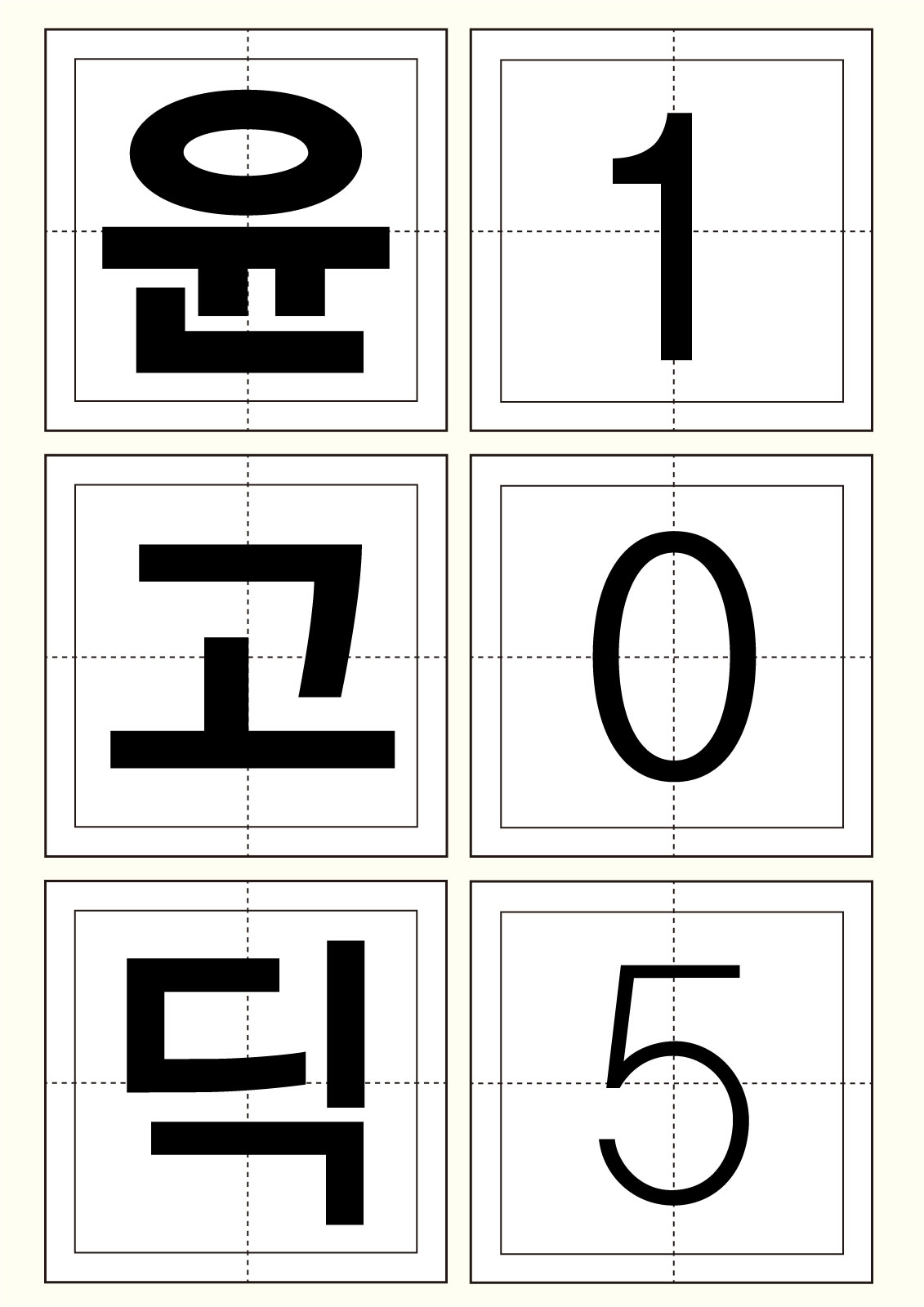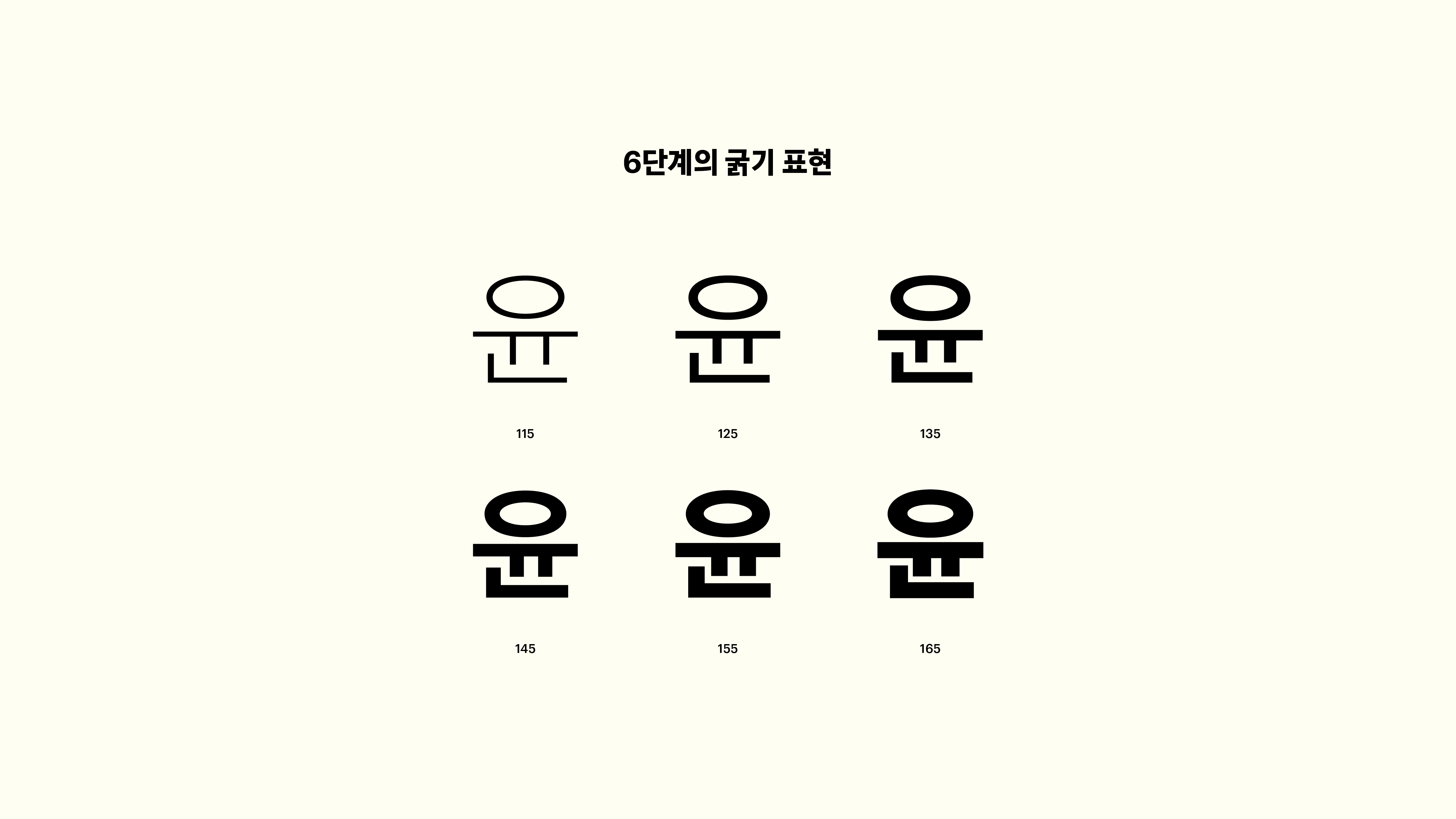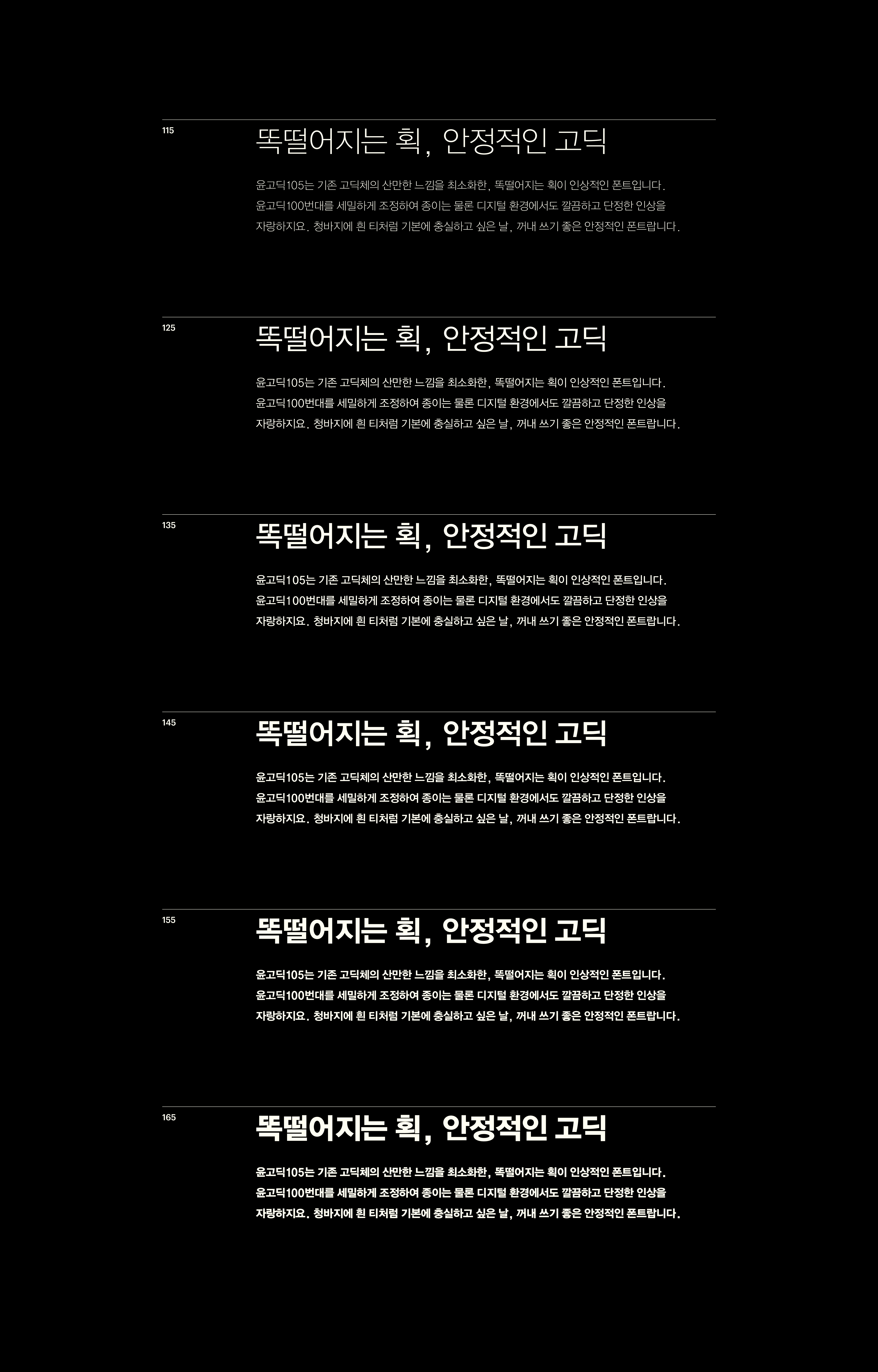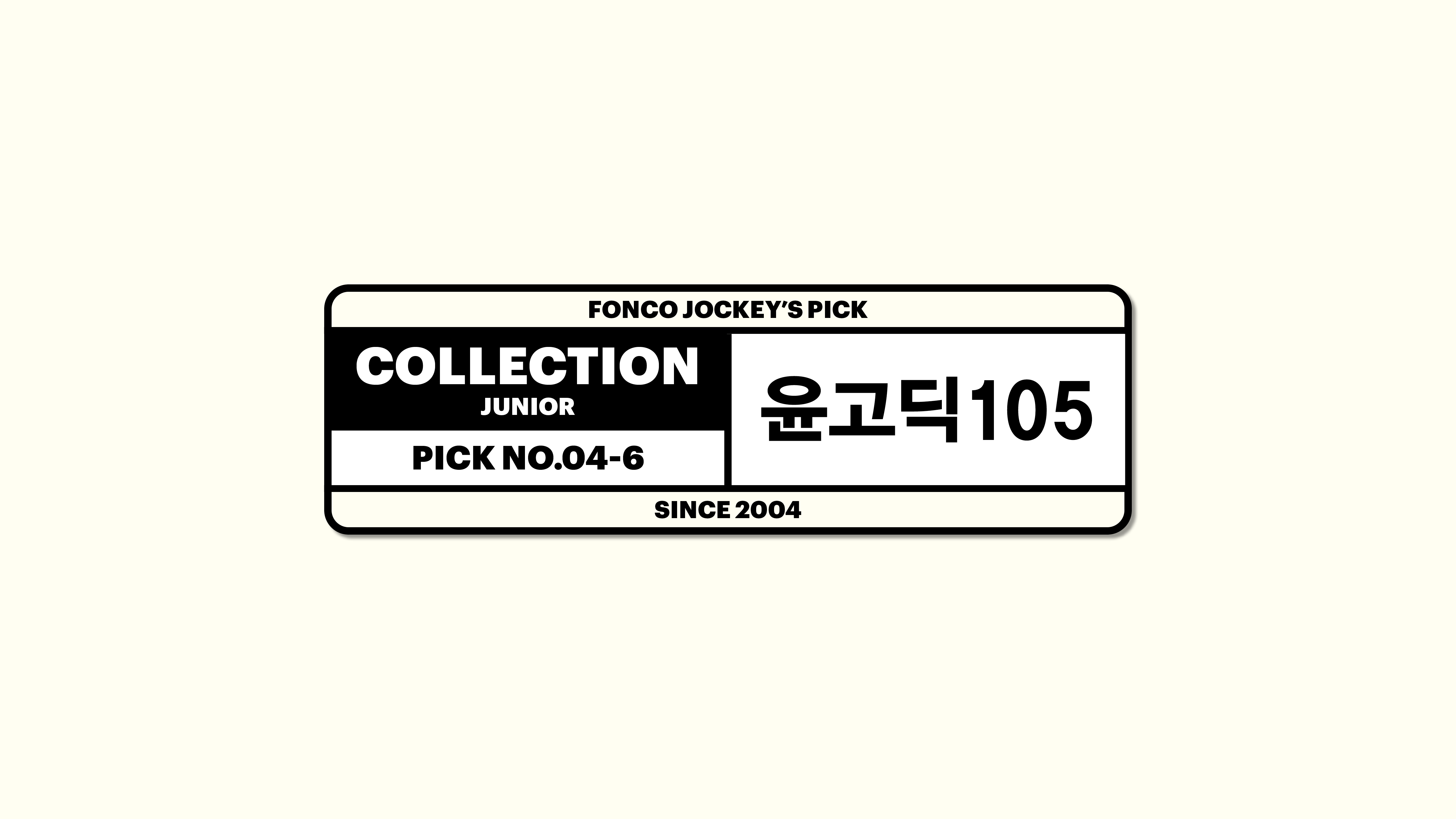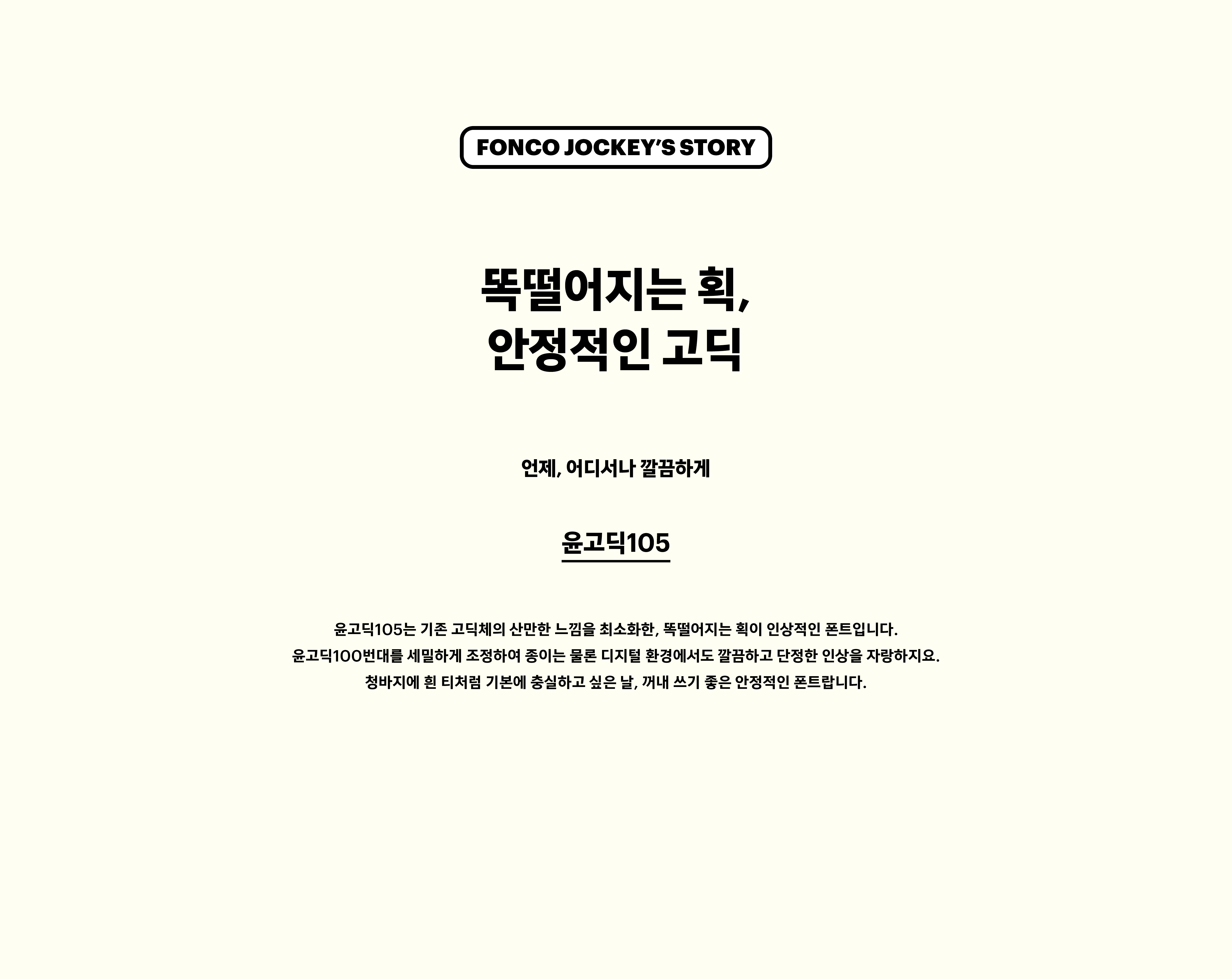
윤고딕 105
2000-2004
Yoon 윤고딕 105
윤고딕105는 기존 고딕체의 산만한 느낌을 최소화한, 똑 떨어지는 핏이 인상적인 폰트입니다. 불필요한 세리프를 제거하여 종이는 물론 디지털 환경에서도 깔끔하고 단정한 인상을 자랑하지요. 청바지에 흰 티처럼 기본에 충실하고 싶은 날, 꺼내쓰기 좋은 안정적인 폰트랍니다.